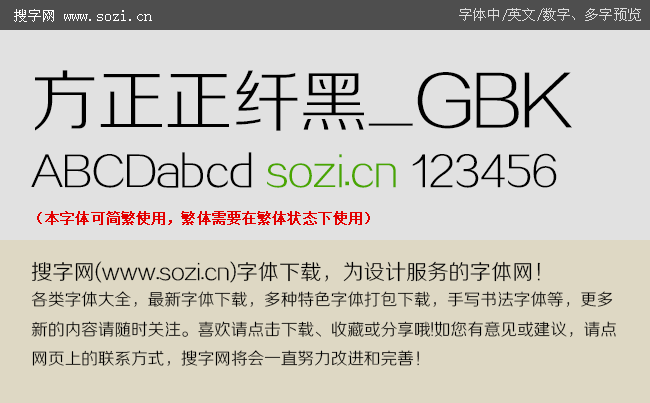
方正正纤黑_GBK
搜字网提供方正正纤黑_GBK中文艺术字体下载,正黑体取传统黑体结构,笔形全部采用平行、垂直与弧度的流线形设计,简洁易识、美观大方,具有个性,加之镜像对称的现代构成形式,达到庄重与简洁有机融合、设计感与阅读功能兼备的最终效果。适合书籍排版,报纸排版,海报设计,包装设计等广告设计场合应用。